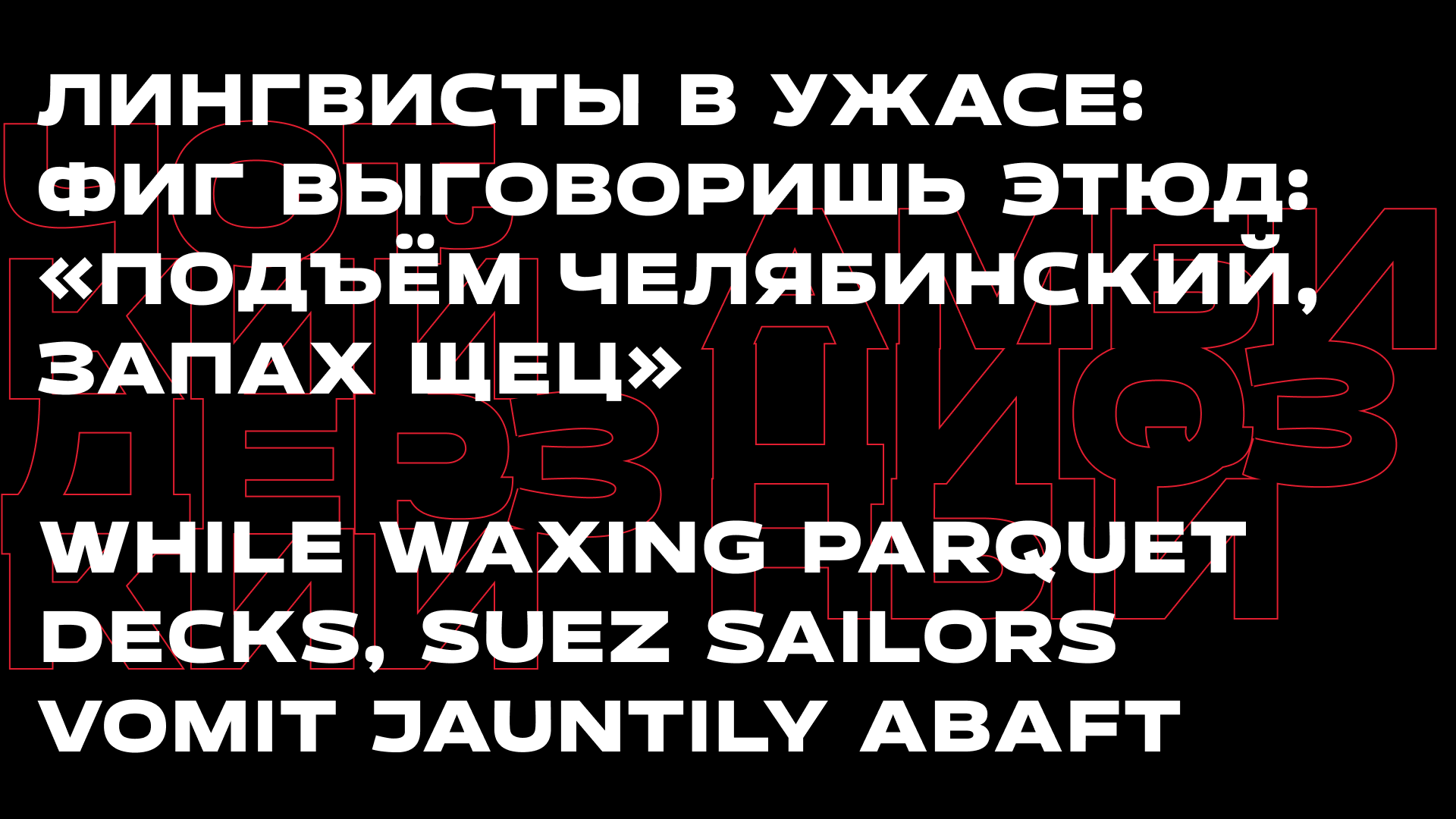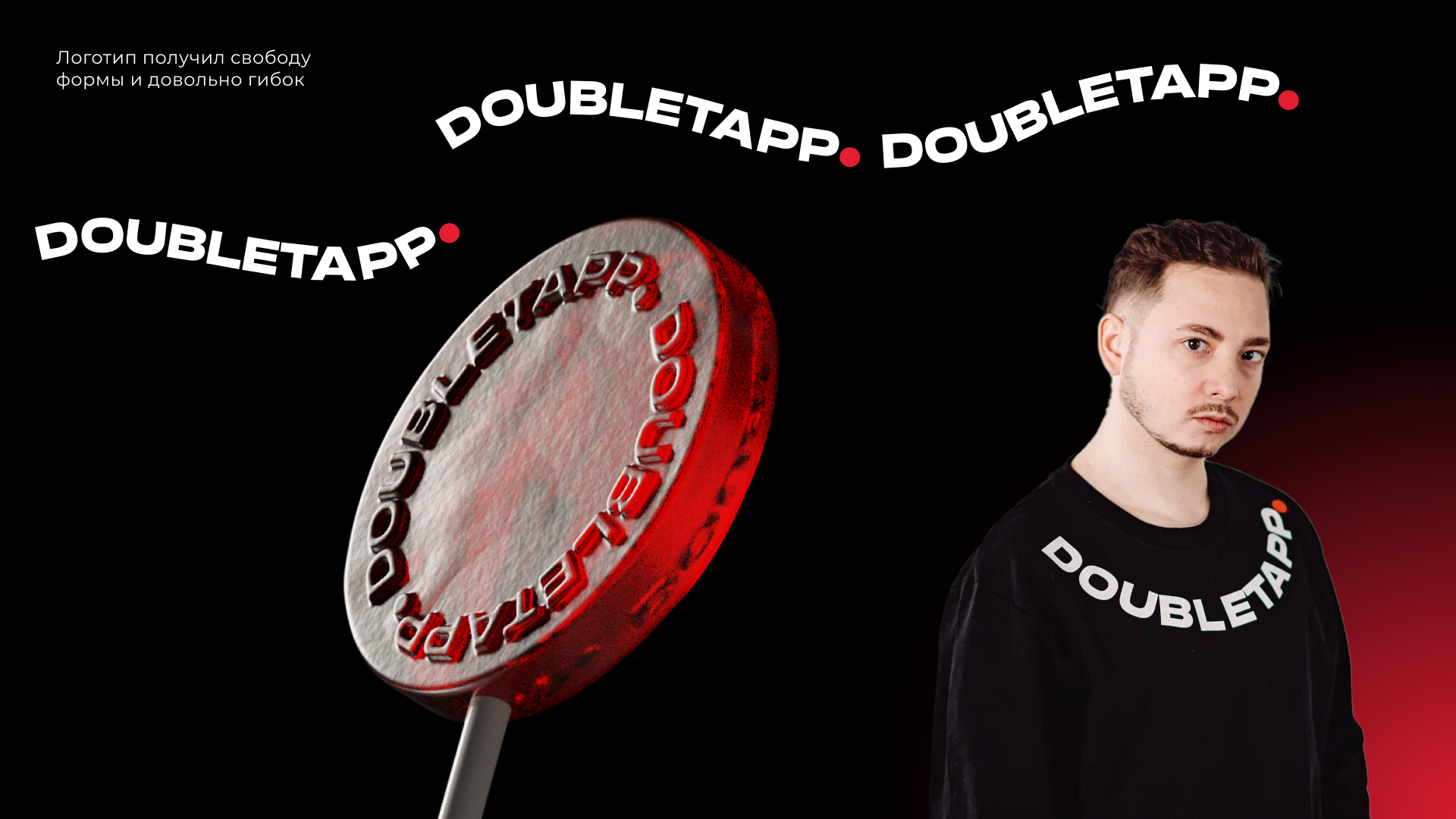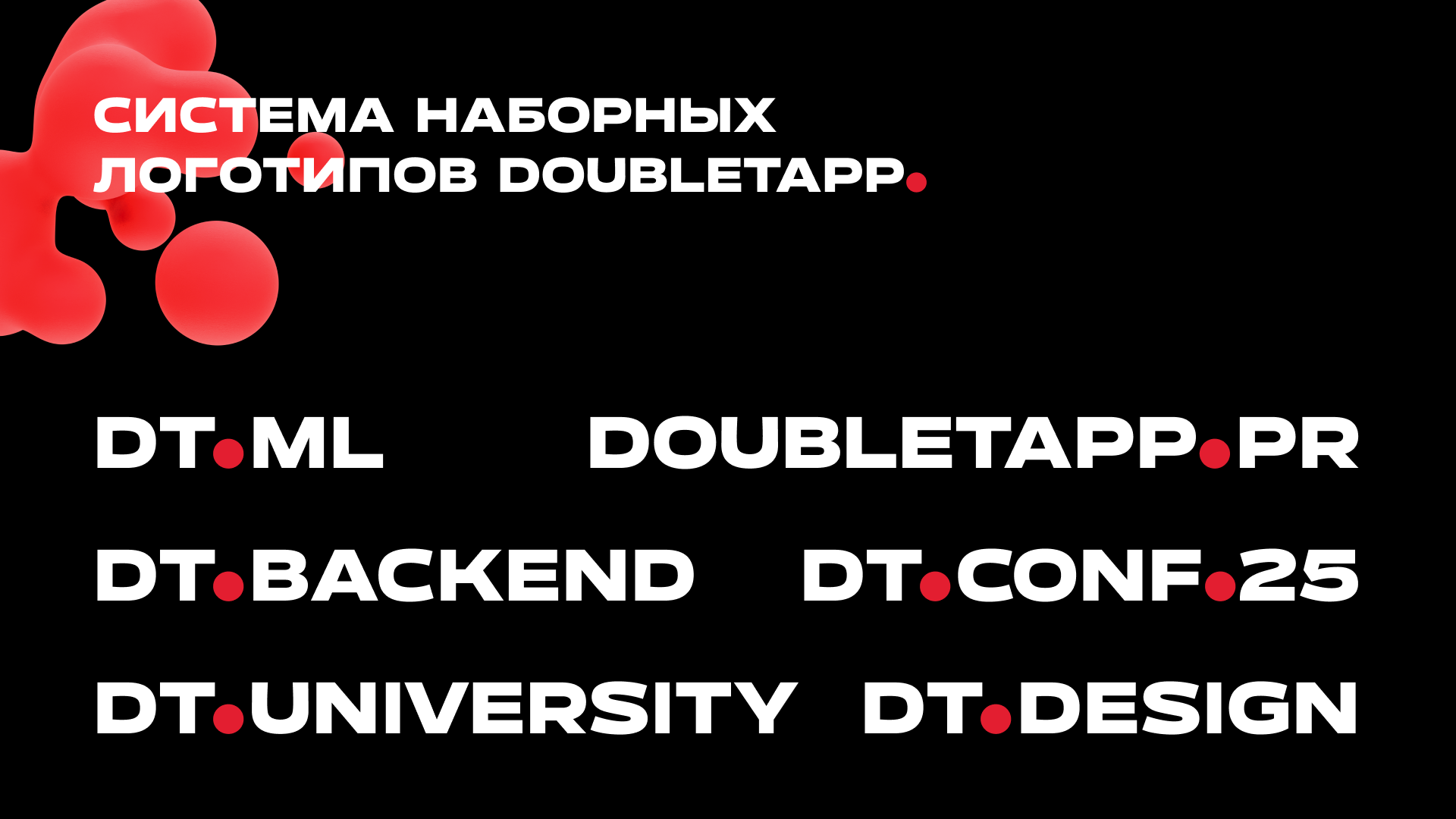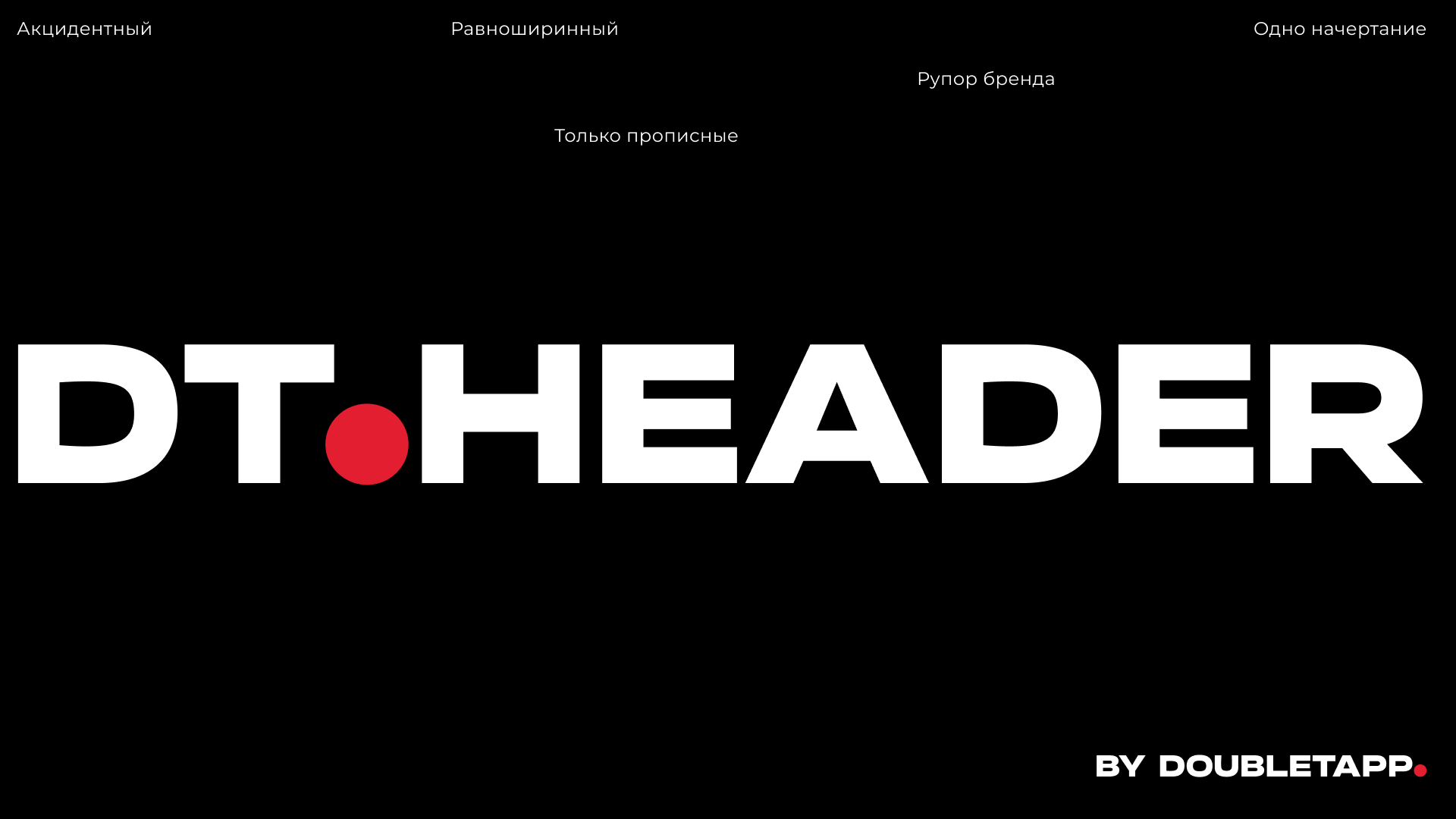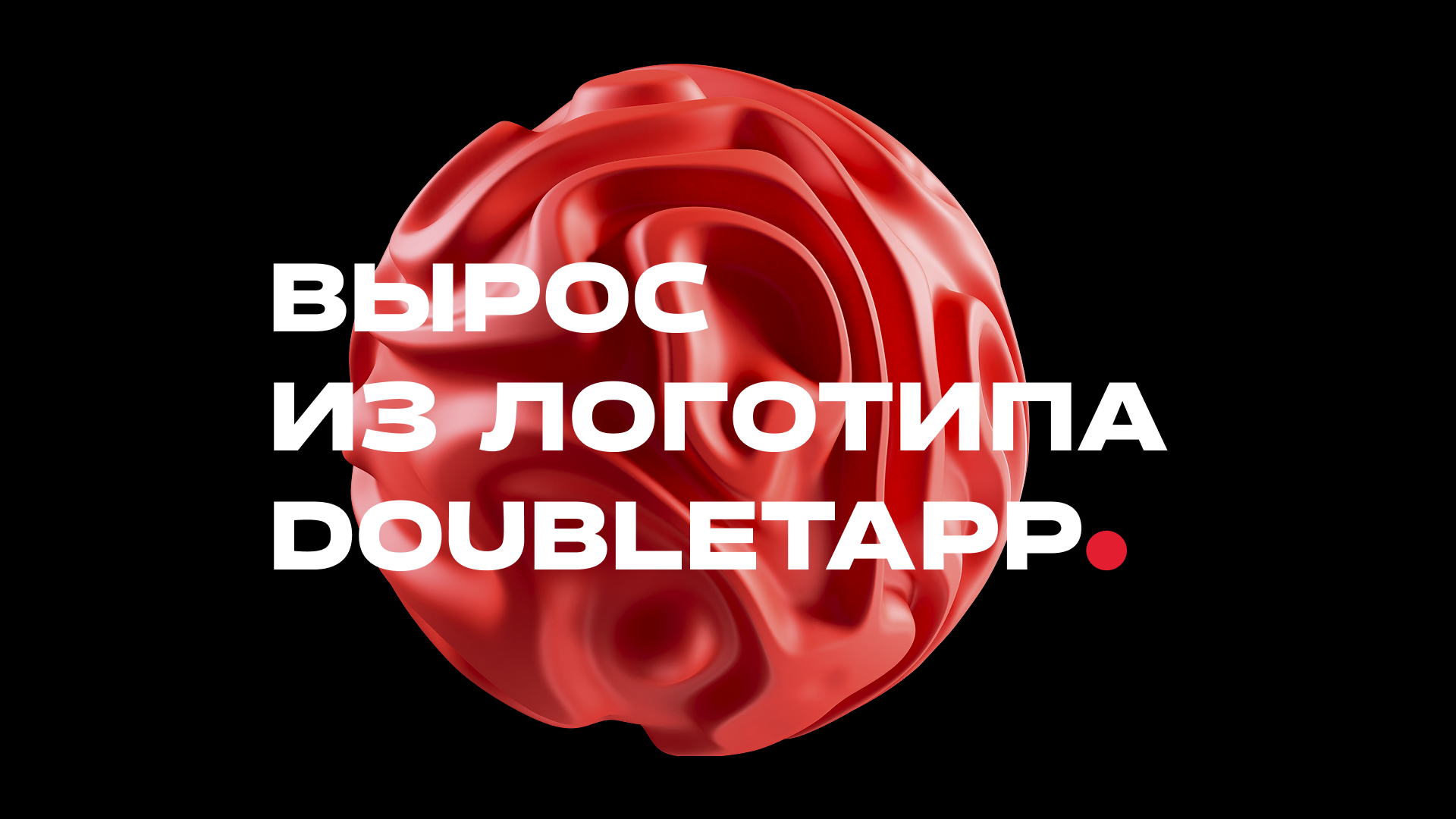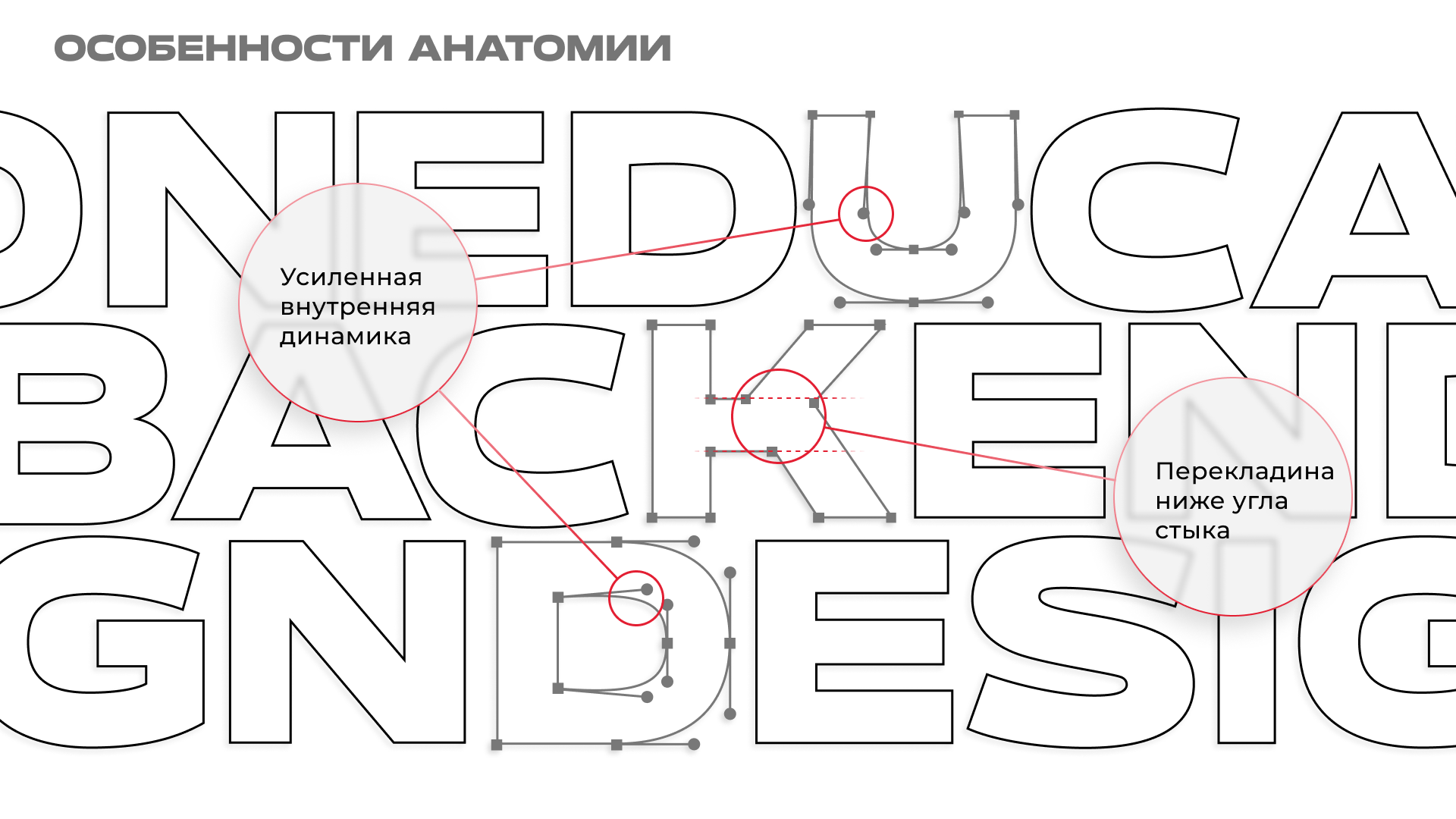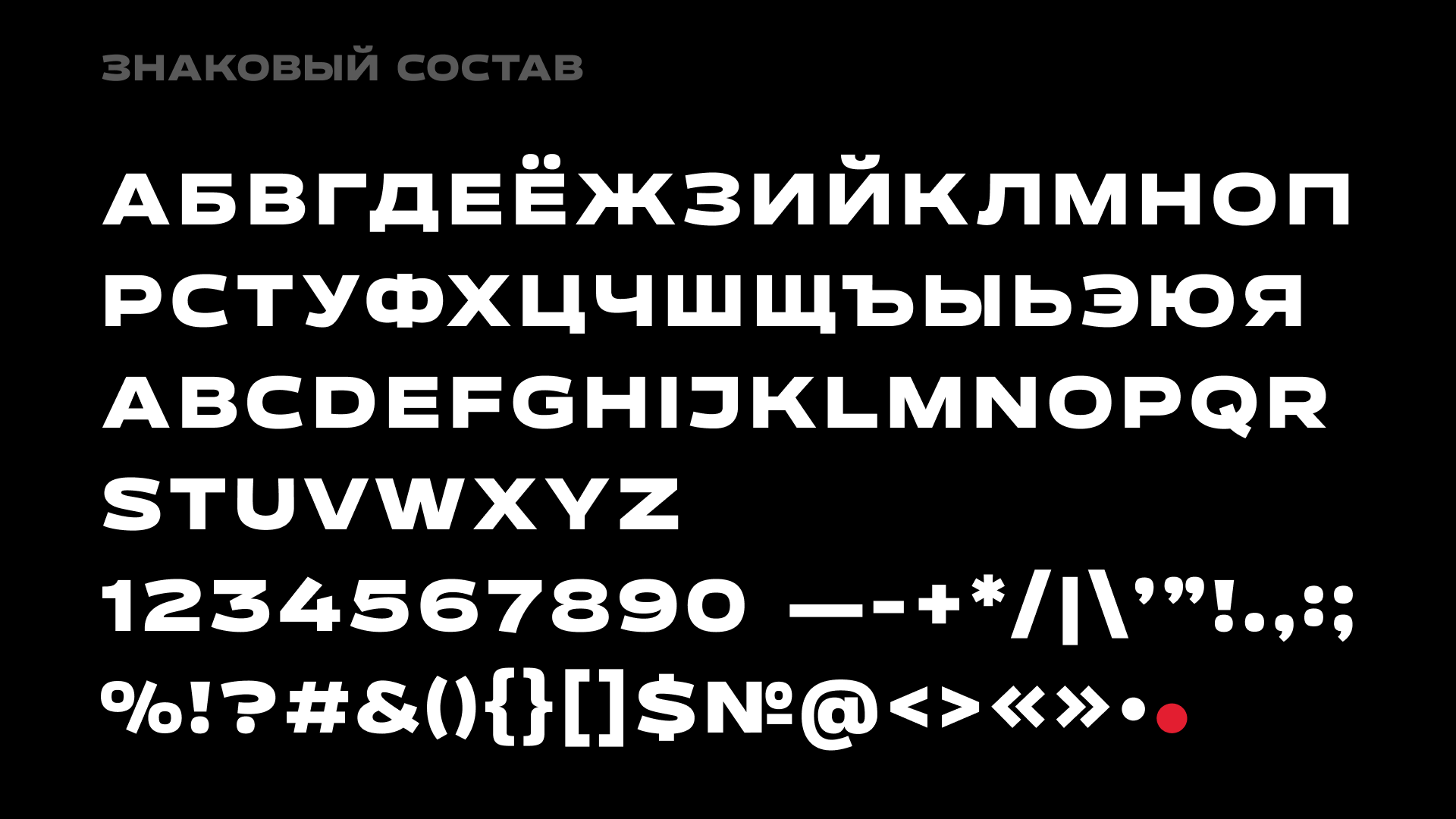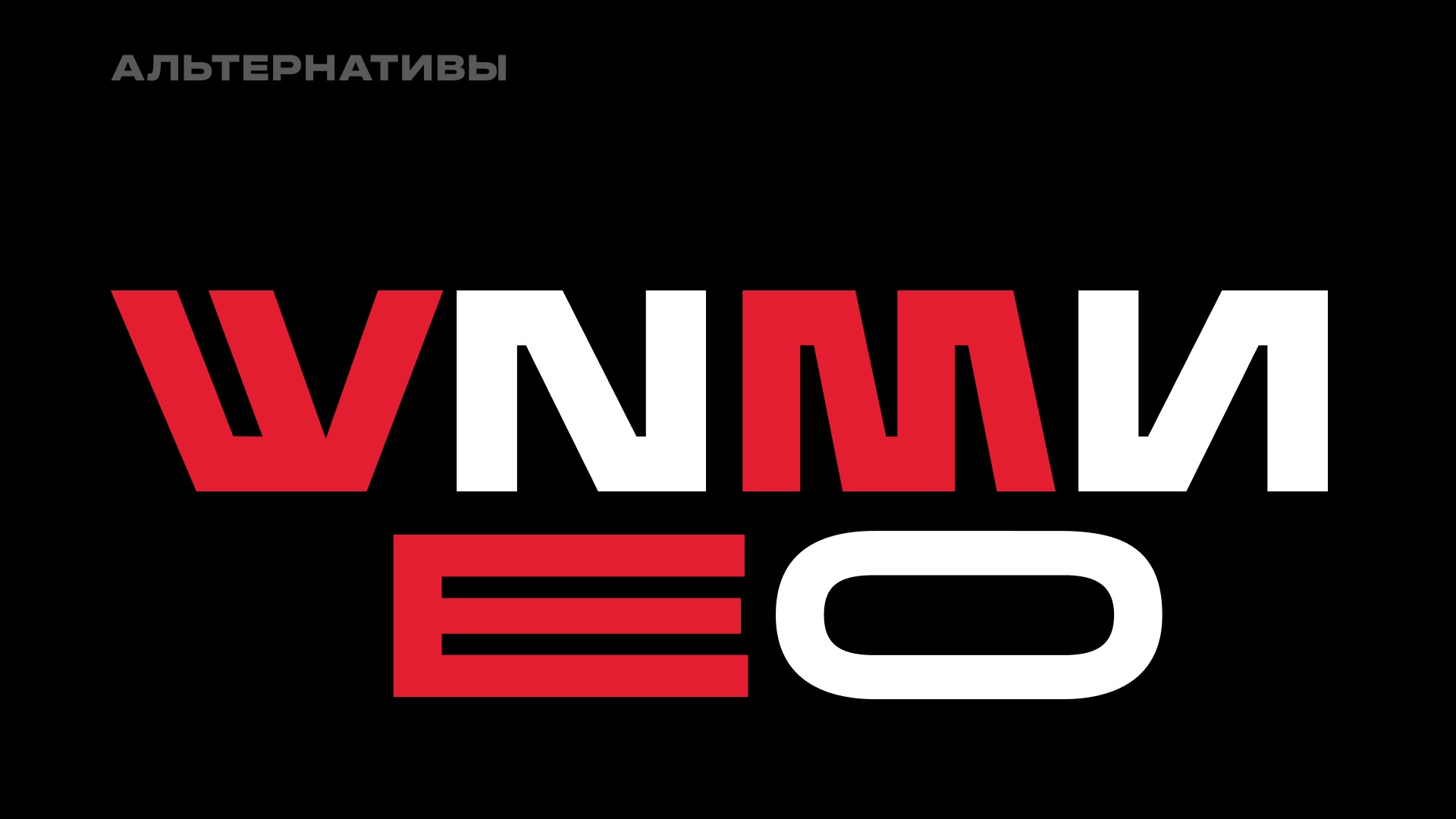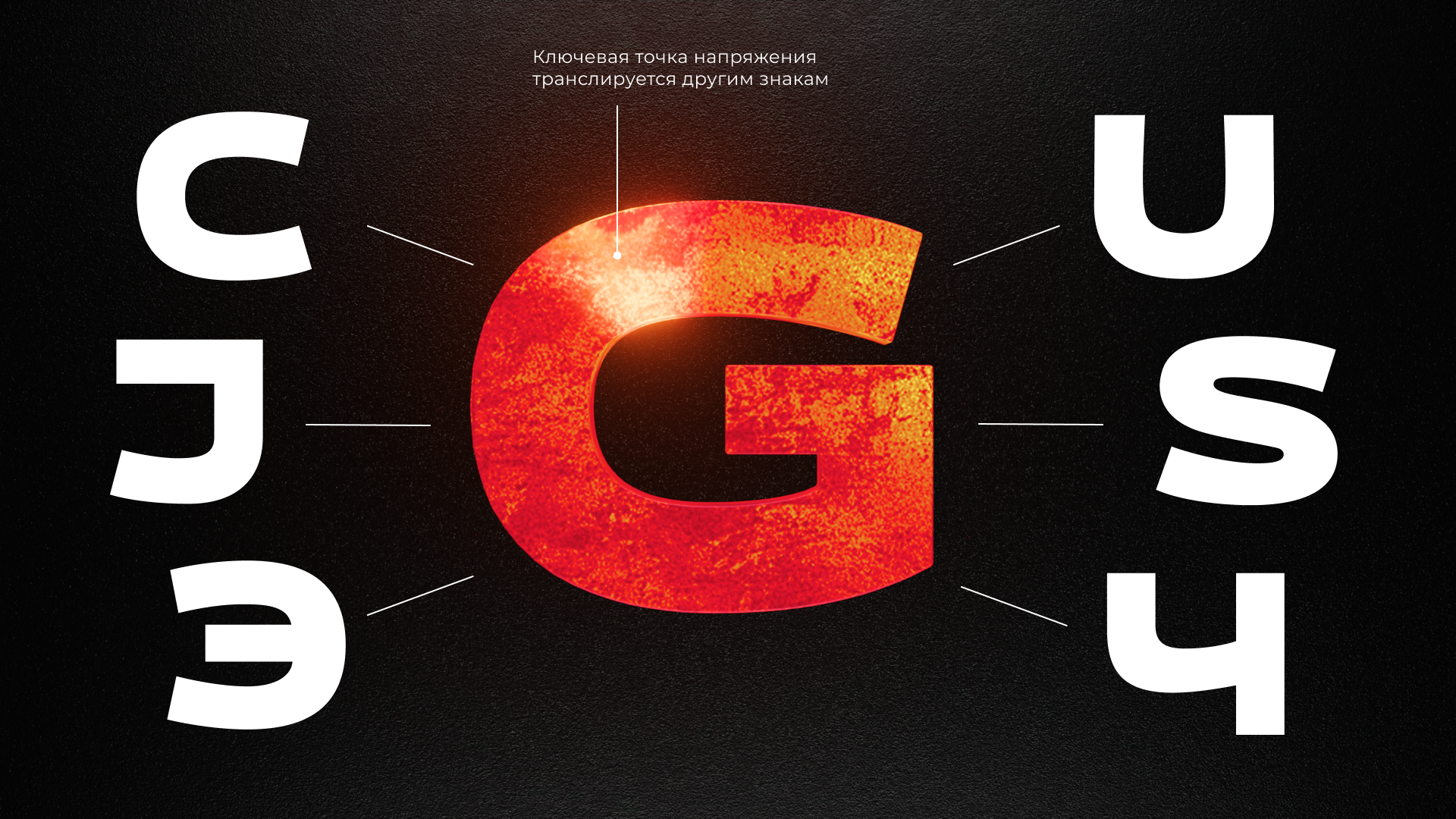
Заказной шрифт
DT.HEADER
Описание работы
DT.HEADER мы начали создавать, когда Doubletapp пересобрал себя заново и решил заявить об этом миру. Мы поняли простую вещь: всё, что мы делаем, мы делаем на совесть и с душой. Мы бросаем вызовы самим себе, всегда предлагаем чуть больше, чем ждут, и ставим собственный знак качества: «Сделано в Даблтап. Точка».
Сначала был логотип. Мы хотели, чтобы он звучал как боевой месседж. Но оказалось, что логотипу мало быть словом. Он хотел стать больше: фразой, заголовком, мемом, стикером. В итоге он стал шрифтом. Теперь любой наш продукт можно подписать DT.HEADER — и это будет рупором бренда.
DT.HEADER — акцидентный, дерзкий, амбициозный. У него открытая апертура (мы не держим фигу в кармане), широкие альтернативные глифы, платформенные соединения диагоналей. Его форма мощная и устойчивая, приквадраченная. Его оружие — иллюстративность: мы сознательно ставим ее выше удобочитаемости. Он работает в крупном кегле и не боится быть хулиганом — потому что кто заметит твою правду, если ты слишком скромный?
В шрифте есть кириллица, латиница, цифры, дополнительные символы. Хочешь, код набирай, хочешь — формулу, инструментов хватит.
Семейство кодерских символов в фирменных цветах мы превратили в самостоятельный выразительный инструмент — они маркируют страницы сайта и соцсетей, внутреннюю документацию и CRM, а еще оживляют мерч: плакаты, кружки, баннеры, таблички, визитки. Зачем давать им столько свободы? Потому что Doubletapp разрабатывает сложные IT-решения, и наша айдентика должна транслировать не только «что» мы делаем, но и «как» мы это делаем: изобретательно, ярко, рассматривая под разными неожиданными углами.
Есть и еще один знак, которым мы маркируем свои коммуникации — фирменная точка. Красный шар живет как независимый элемент. Мы используем его и вместе с текстом, и с кодерскими знаками, и как отдельный символ присутствия бренда.